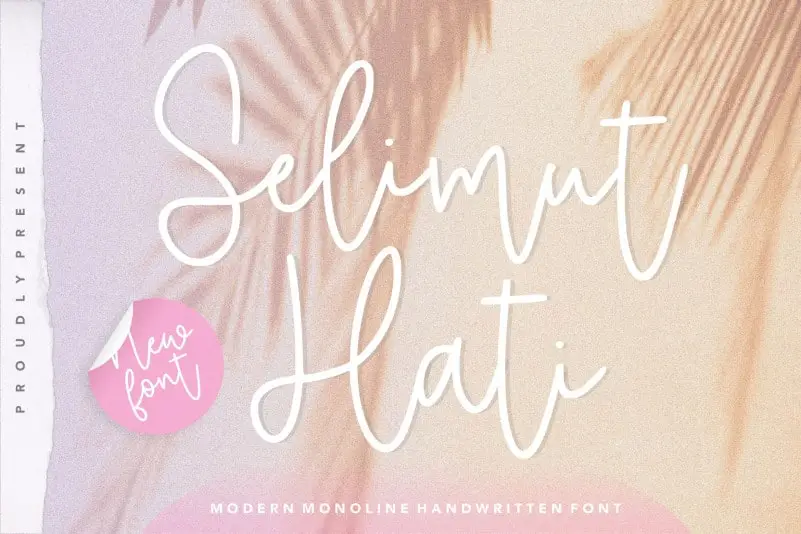
Selimut Hati Monoline Handwritten Font – Download Grátis
A ‘Selimut Hati’ Monoline Handwritten Font é perfeita para se estilizar com uma pitada artesanal enquanto mantém a simplicidade e clareza necessárias para qualquer projeto visual, seja ele de branding ou embalagem de produto, revista ou mídia social. Sua natureza delicada e elegante combina harmoniosamente com temas como weddings e projetos que valorizam o texto acima do fundo. Com um toque suave e autêntico, esta fonte manuseia qualquer projeto visual em uma linha única, oferecendo um estilo personalizado sem comprometer a facilidade de uso ou resolução. Seja para destacar uma marca, complementar conteúdo editorial ou criar um ambiente de celebração, ‘Selimut Hati’ traz uma mão humanizada à sua arte digital.